2023 年 21 種最佳鄉村字體(免費和付費)
但在我們深入研究字體之前,您可能會想,“為什麼要使用質樸的字體?” 嗯,質樸的字體是設計師中的流行選擇,因為它們能喚起一種溫暖、懷舊和真實的感覺,使它們非常適合具有復古或手工美感的項目。
現在,我們來談談您對本文有何期望。 我們精心挑選了 21 種最佳鄉村字體列表,這些字體不僅具有視覺吸引力,而且易於訪問且用途廣泛。 從手寫腳本到粗體襯線字體,我們都能滿足您的需求。
因此,無論您是在製作婚禮邀請函、徽標設計還是網站標題,您都會找到完美的質樸字體來增強您的專案。
本文的核心是,我們旨在為您提供質樸字體世界的全面介紹。 我們將探索每種字體的獨特特徵,分享如何在設計中最好地利用它們的技巧,甚至提供成功融入這些字體的現實項目的範例。
因此,準備好受到啟發並發現能夠真正將您的設計轉變為藝術作品的字體。 話不多說,讓我們直接開始探索 21 種最好的鄉村字體!
希望為您的設計專案增添一絲質樸魅力? 別再猶豫了! 我們最好的優質鄉村字體系列一定會激發您的設計靈感並將其提升到一個新的水平。 請參閱下面這些令人難以置信的字體,並準備好釋放您的創造力!
農家
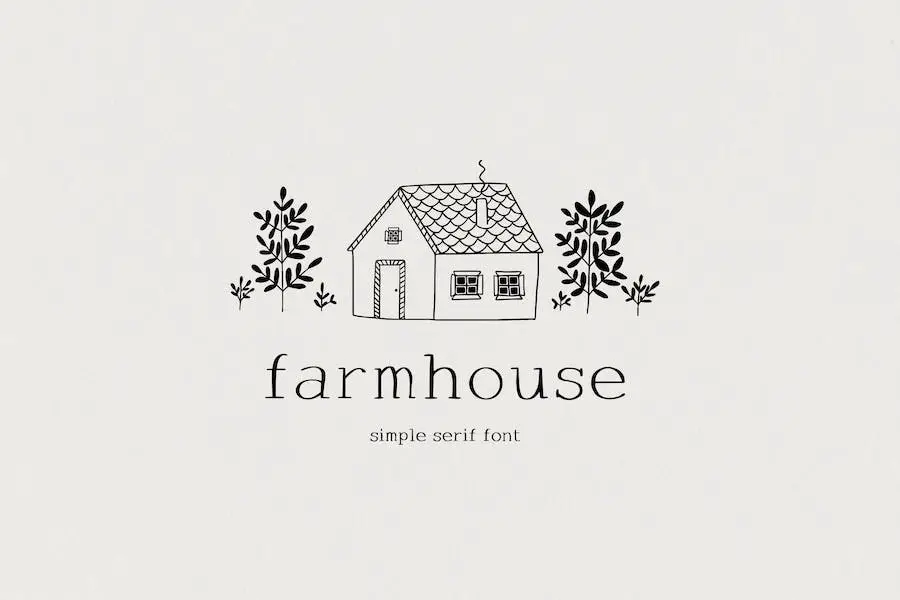
Farmhouse 是一個很棒的顯示襯線字體集合,帶有可愛的插圖。 它非常適合創建徽標、設計卡片、建立您的品牌等等。 準備好愛上它的甜蜜魅力吧。
使用 Farmhouse,您將有多種字體可供選擇,每種字體都有自己獨特的風格和個性。 無論您想要質樸、復古還是手工製作的外觀,這個系列都能滿足您的需求。
您會發現優雅精緻的字體,以及粗糙仿舊的字體,為您的專案提供無限的可能性。
您不僅可以獲得令人驚嘆的字體選擇,而且 Farmhouse 還包括可愛的插圖,可以為您的設計增添額外的魅力。
從花卉元素到農舍圖標,這些插圖可以幫助您將想法變為現實,並使您的專案真正脫穎而出。
貝法洛
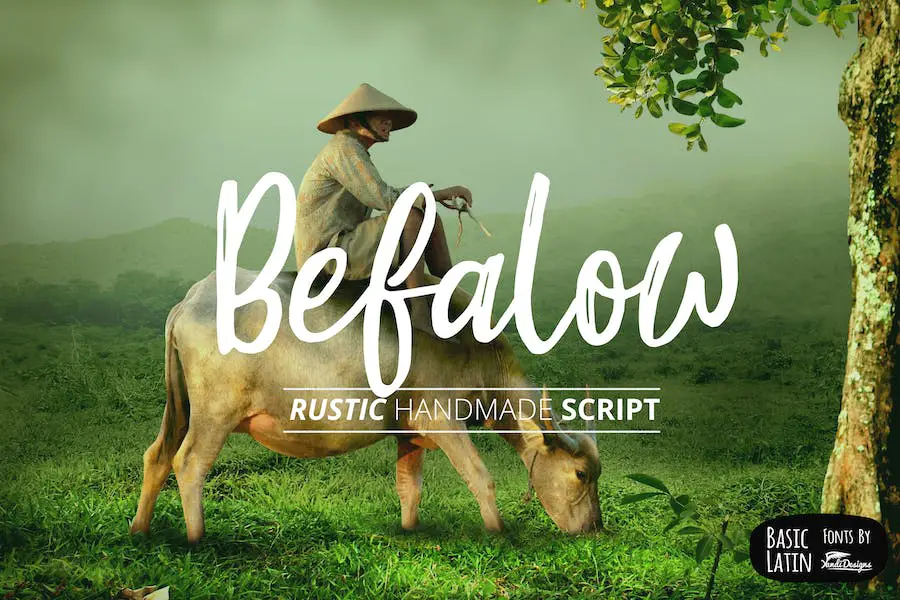
Befalow 是一種簡單的畫筆字體,非常適合各種項目,例如引言、標誌、標題和標題。 憑藉其簡潔優雅的設計,它為任何設計增添了一絲精緻感。
這款字體的畫筆筆觸賦予其質樸而真實的感覺,使其在尋求增強專案視覺吸引力的圖形設計師中特別受歡迎。
無論您是在進行復古風格的設計還是想添加一絲懷舊氣息,Befalow 都是可以將您的願景變為現實的字體。
Befalow 的突出特點之一是它的多功能性。 它可用於廣泛的項目,允許設計師嘗試不同的風格和主題。 它的簡單性和可讀性使其成為印刷和數位設計的絕佳選擇。
Befalow 的另一個特點是它能夠透過刷子般的質感傳達情感和個性。 它為任何設計增添了自然和手工的感覺,使其從通用字體中脫穎而出。
鄉村
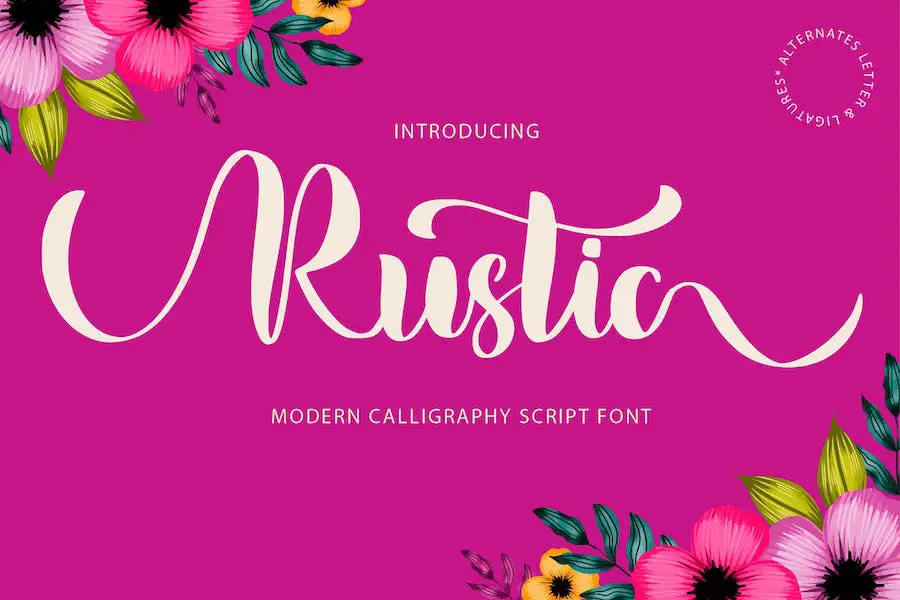
Rustic 是一種現代腳本字體,提供手工製作的拉絲風格。 它非常適合增強婚禮卡、徽標、網站標題、時尚設計等的設計。
憑藉其獨特而美麗的設計,Rustic 為任何項目增添了一抹優雅和魅力。 無論您是在為您的品牌創建令人驚嘆的婚禮邀請函還是時尚的徽標,這種字體一定會給人留下深刻的印象。
Rustic 創作中使用的手工刷漆技術賦予其獨特的藝術外觀。 其流暢而大膽的筆觸為文字增添了個性和個性,使其具有視覺吸引力和吸引力。
質樸醇厚
Rustic Mellow 是一款單線手寫字體,非常適合您所有設計專案的需求。 這種字體以其獨特的風格為您的設計帶來一絲質樸的魅力和優雅。
字體外觀乾淨流暢,易於閱讀,賞心悅目。 其單線結構賦予其一致且有凝聚力的外觀,確保您的設計具有專業的外觀。
憑藉其手寫的感覺,Rustic Mellow 為您的專案增添了個人風格,營造出真實和溫暖的感覺。
Rustic Mellow 的突出特點之一是它能夠喚起懷舊感。 它讓人想起舒適的小屋、劈啪作響的篝火和大自然的美麗。 這使其成為鄉村或自然主題項目的完美選擇。
鄉村
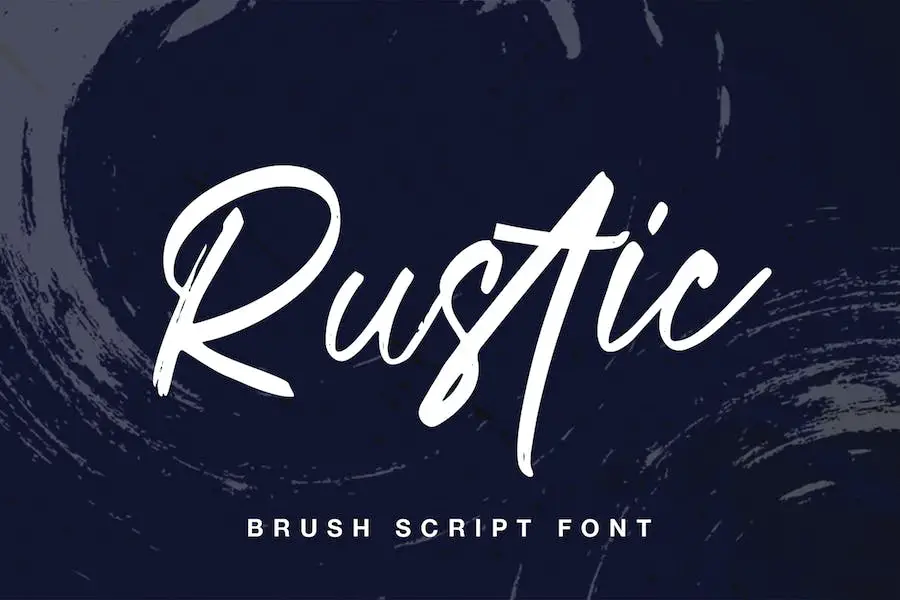
Rustic 是一種現代簽名字體,可為任何設計項目增添一絲優雅和精緻。 憑藉其獨特而質樸的風格,這種字體非常適合希望增強其項目並賦予其更有機和自然感覺的平面設計師。
Rustic 的突出特點之一是它的多功能性。 無論您是在設計商標、品牌材料,甚至是社群媒體圖形,這種字體都能夠提升您的設計並使其真正獨一無二。
其質樸的魅力和手工製作的感覺將吸引觀眾的注意力並留下持久的印象。
Rustic 的另一個重要屬性是它的可讀性。 儘管其設計獨特而複雜,但這種字體仍然易於辨認,確保您的訊息得到有效傳達。
它在風格和功能之間取得了完美的平衡,使其成為想要發表聲明但又易於理解的設計師的首選。
鄉村復興
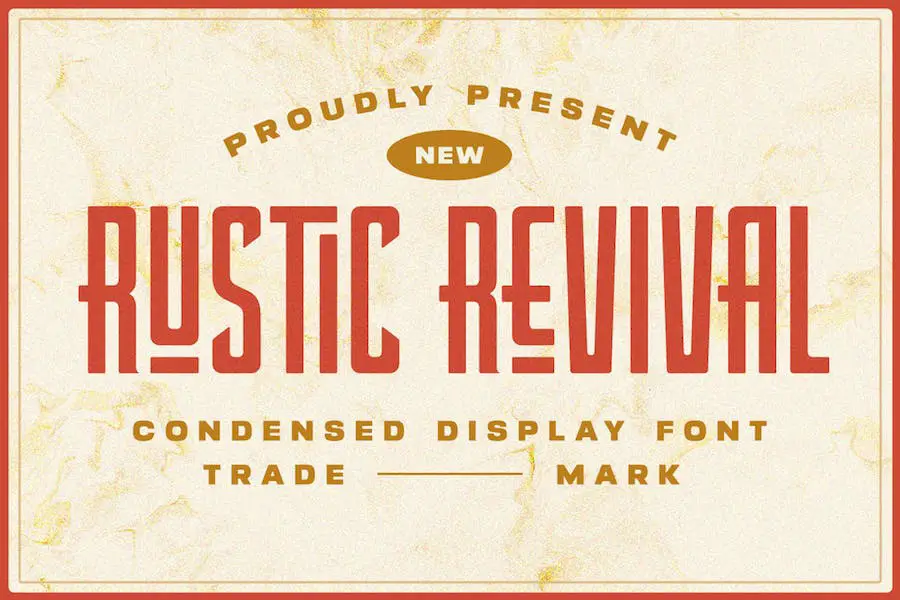
隆重介紹 Rustic Revival,這是一款非常適合希望增強專案整體設計的平面設計師的字體。 透過其連字選項,該字體可讓您創建獨特的字元組合,為您的文字添加視覺上有趣的感覺。
Rustic Revival 中的連字不僅使您的文字在視覺上更具吸引力,而且還改善了設計的整體流程。 透過結合這些獨特的角色組合,您可以立即使您的專案脫穎而出。
無論您是為 Canva 還是 Cricut 開發項目,Rustic Revival 都是為您的設計增添質樸和真實風格的完美字體。 其質樸的風格增添了溫暖和魅力的感覺,非常適合需要復古或懷舊感覺的項目。
這種字體用途廣泛,可用於各種設計項目,從邀請函和徽標到社交媒體圖形和網站設計。 其易讀性可確保您的訊息清晰地傳達給受眾。
質樸印花
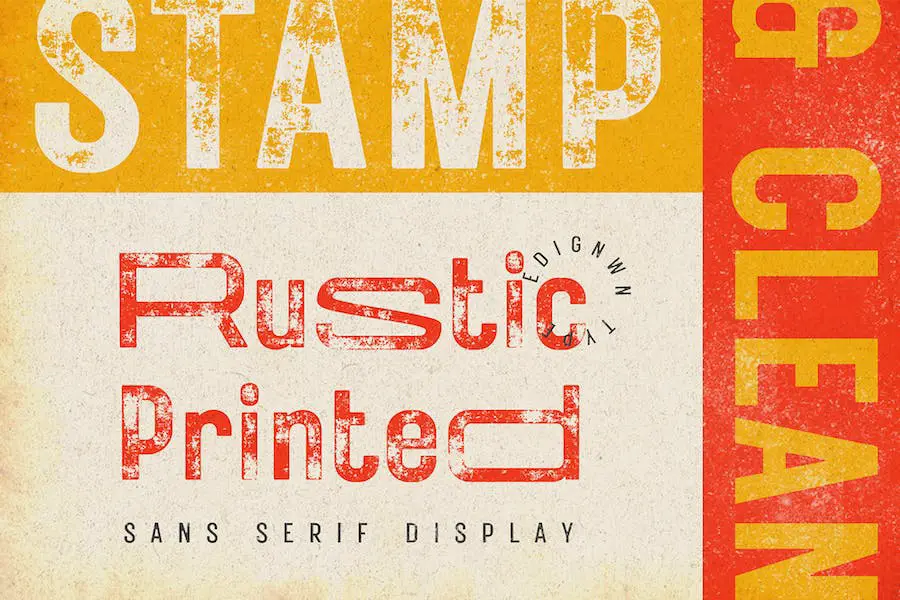
Rustic Printed 是一種時尚的字體,為您的設計帶來復古和鄉村的感覺。 它具有無襯線顯示和兩種風格的字體 - 常規和郵票。 憑藉其質樸的主題,這種字體非常適合為您的專案增添一絲懷舊之情。
Rustic Printed 的常規字體乾淨而經典,提供簡單而優雅的外觀。 它非常適合創建需要復古風格的標題、標題和徽標。 無論您是設計海報、品牌材料還是邀請函,這種字體都會為您的作品增添獨特的魅力。
Rustic Printed 的郵票字體為您的設計增添了紋理和仿舊效果。 它非常適合創建復古標籤、徽章或任何需要真實復古外觀的藝術品。 郵票風格營造出一種質樸的氛圍,為您的項目帶來個性和深度。
質樸的真相
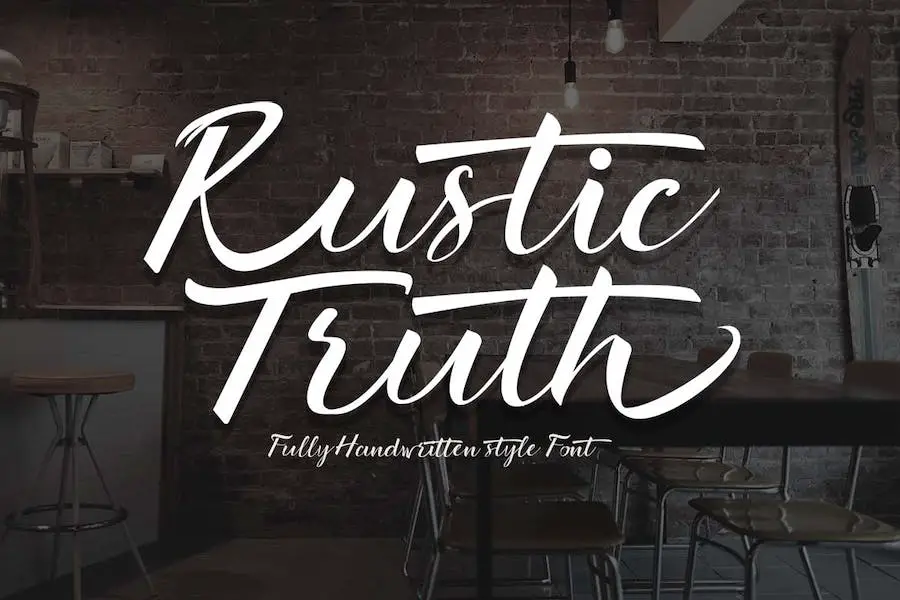
Rustic Truth 是一種美麗而優雅的腳本字體,被稱為“It”。 它散發出獨特而可愛的感覺,使其成為想要增強項目設計的平面設計師的完美選擇。
此字體集有 21 種最佳鄉村字體可供選擇,提供了多種選項來提升任何設計。 無論您是在從事復古風格的項目,還是希望為您的設計增添一絲質樸魅力,這個字體集都能滿足您的需求。
Rustic Truth 系列中的每個字體都有其獨特的屬性,使其與眾不同。 從手繪筆觸到複雜的書法,這些字體為您的設計帶來個性和個性。
它們捕捉了質樸之美的精髓,細節喚起了溫暖和懷舊的感覺。 無論您是設計徽標、製作海報還是製作婚禮請柬,這些字體都會增添一絲真實感和魅力。
魯斯泰因
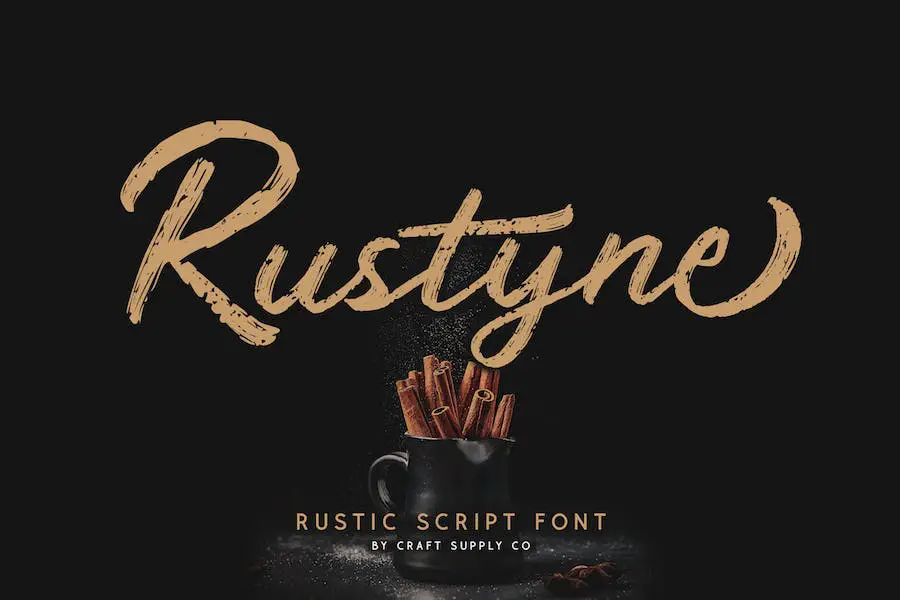
Rustyne – Rustic Script 字體為您的設計項目帶來真實手寫的精髓。 憑藉其手繪風格,這種字體為任何設計增添了質樸和迷人的觸感。 該字體的靈感來自於自然的手寫體,給人一種有機而真實的感覺。
無論您是在製作徽標、海報還是任何其他需要鄉村風格的項目,Rusyne 都是完美的選擇。
這款腳本字體捕捉了真實手寫的精髓,為您的設計帶來個性化和獨特的觸感。 其流暢的筆觸和不完美的邊緣模仿了鋼筆在紙上的自然移動,創造出真正的手寫外觀。
Rustyne 的設計旨在喚起懷舊感和真實感,使其成為需要質樸和復古感覺的項目的理想選擇。
Rustyne 的突出特點之一是它的多功能性。 它適用於各種設計環境,從質樸的婚禮邀請函到咖啡店品牌。 該字體易於使用且易於閱讀,適用於標題和正文。
Rustyne 能夠適應不同的設計風格,讓您可以自由地進行實驗並創造令人驚嘆的視覺效果。
空氣佩納
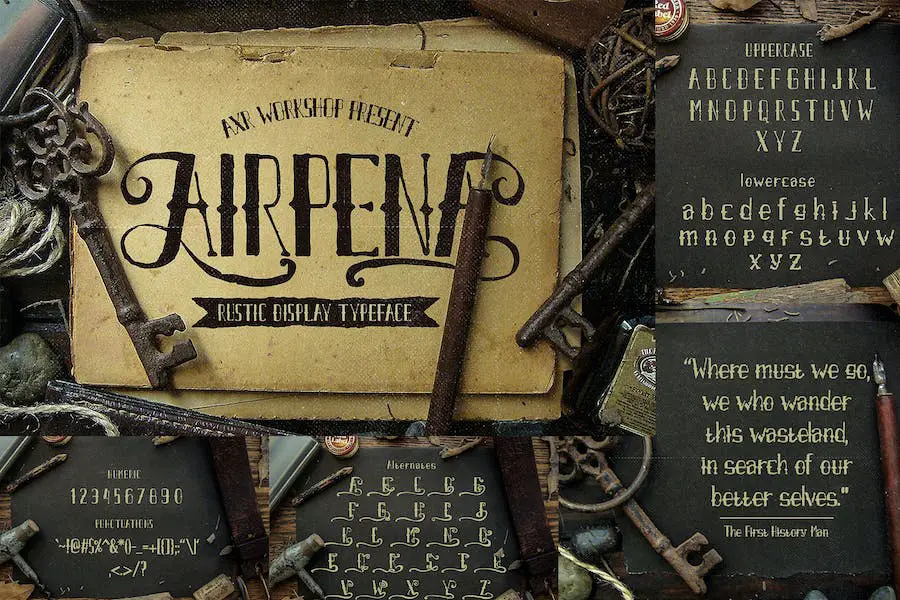
Airpena 是一款引人注目的質樸顯示字體,可為任何設計項目增添一抹復古魅力。 憑藉其獨特的手工製作感覺,這種字體非常適合想要提升其項目並賦予其質樸和懷舊氛圍的圖形設計師。
Airpena 的主要特徵之一是其真實且飽經風霜的外觀。 這些字母看起來破舊而做舊,彷彿經受住了時間的考驗。 這為任何設計增添了個性和個性,使其在人群中脫穎而出。
此外,Airpena 還提供各種字形和替代字母形式,使設計師能夠創建客製化且獨特的印刷組合。 從花體到連字,該字體為創意表達提供了無限的可能性。
無論您是在製作復古標誌、復古海報還是質樸的婚禮請柬,Airpena 都能滿足您的需求,讓您的願景成為現實。
鄉村車站
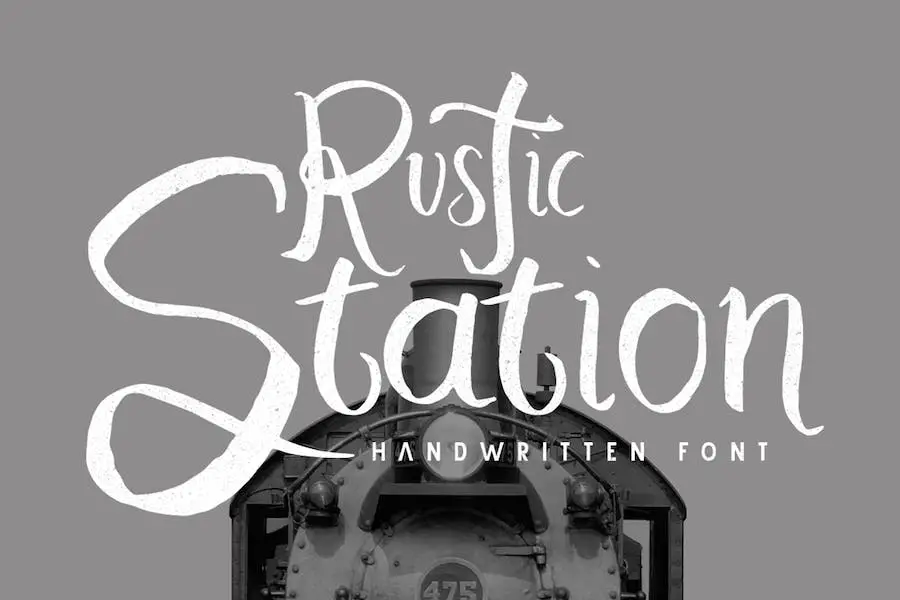
Rustic Station 是一種可為您的設計帶來純正手工製作風格的字體。 無論您是在創建文具、徽標還是其他任何東西,這種字體都會為您的項目帶來您想要的獨特而迷人的外觀。
使用 Rustic Station,您將能夠輕鬆地為您的設計添加質樸和復古的感覺。
對於想要為專案添加個性和特色的平面設計師來說,這種字體是完美的選擇。 憑藉其手工製作的外觀,Rustic Station 將使您的設計脫穎而出。
它用途廣泛,可用於從婚禮邀請函到包裝設計的廣泛應用。
Rustic Station 的突出特點之一是其真實性。 字體捕捉了手工設計的精髓,使其成為任何想要創造復古或質樸感覺的人的絕佳選擇。 它為您的項目增添了一絲溫暖和懷舊的氣息,賦予它們獨特的個性化風格。
質樸的農舍
Rustic Farmhouse 是一種可愛而休閒的畫筆字體,可為您的設計增添時尚氣息。 這種多功能顯示字體非常適合為您的專案增添質樸和手工製作的感覺。 憑藉其刷子般的筆觸,它為任何設計提供了獨特和個性化的觸感。
字體具有休閒和手寫的風格,為您的設計帶來溫暖和真實的感覺。 無論您是在設計徽標、品牌材料,甚至是產品包裝,Rustic Farmhouse 都可以幫助增強整體設計並使其脫穎而出。
鄉村農舍的突出特點之一是它的多功能性。 它適用於從婚禮邀請函到社交媒體圖形的各種設計項目。 此字體的畫筆筆觸增添了質感,讓您的文字感覺更加有機和手工製作。
質樸的農舍
Rustic Farmhouse 是一款質樸的字體組合,非常適合各種設計專案。 憑藉其迷人的復古風格,它為任何設計增添了獨特的個性。
無論您是在設計標誌、包裝,甚至是網站,這種字體都會提升您的專案並賦予其質樸和懷舊的氛圍。
鄉村農舍的突出特點之一是它的多功能性。 字體組合包括腳本字體和無襯線字體,可讓您混合它們以創建不同的外觀和風格。
腳本字體具有漂亮的花體和連字,為您的設計增添額外的魅力。 另一方面,無襯線字體乾淨簡單,非常適合標題和標題。
這對字體的另一個重要特點是它對細節的關注。 每個角色都是精心手工製作的,確保它們無縫地融合在一起。
另外,嘗試不同的字體大小和字母間距以找到完美的平衡。
結論
在本文中,我們探討了平面設計師可以用來增強其專案的 21 種最佳質樸字體。 我們討論了每種字體的獨特功能以及它們如何為任何設計增添一絲質樸魅力。